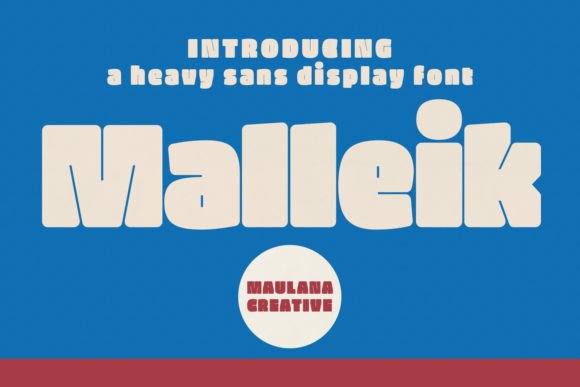
Malleik
Malleikのような高品質の素材をお探しの場合、このプレミアムパッケージはクリエイティブなプロジェクトに素晴らしい選択です。
精密に作られたMalleikは、クリーンなベクター、滑らかなタイポグラフィ、そして安心のための商用ライセンスを提供します。
POD(オンデマンド印刷)製品、結婚式の招待状、またはソーシャルメディアのグラフィックを作成している場合でも、Malleikは理想的です。